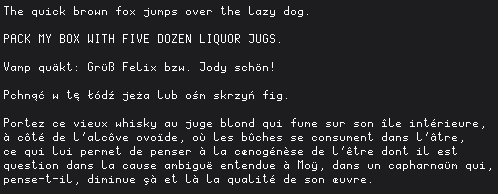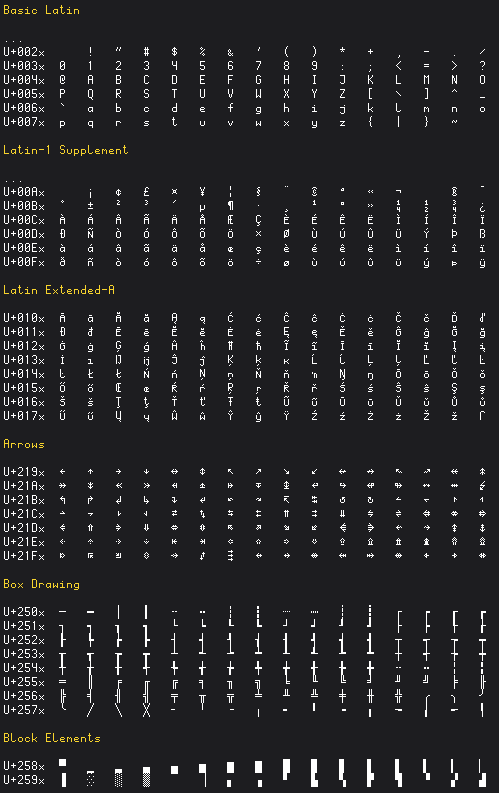
免费的微型Unicode等宽像素字体素材,一种是4×8的小字体,另一种是7×14的大字体。
小字体尽可能小,但仍能保证所有标准ASCII字符清晰可辨。大字体稍大一些,以便容纳其他语言的字符。
小字体
这是一个仅支持英文的(ASCII)字体。字符图块为 4×8 像素,但大多数字符可以容纳在 3×5 像素内。图像文件包含 128 列和 4 行字符(包括空格)。
按顺序排列的Unicode块
U+0000-U+007F,基础拉丁语
U+2190-U+21FF,箭头
U+2500-U+257F,箱体图
U+2580-U+259F,块元素
大字体
此字体包含来自各种“拉丁”字符集的额外字符,因此除了英语之外,它还可以用于多种语言。字符图块尺寸为 7×14 像素,但大多数字符可以容纳在 5×9 像素的范围内。图像文件包含 128 列和 5 行字符(包括空格)。
按顺序排列的Unicode块
U+0000-U+007F,基础拉丁语
U+00A0-U+00FF,拉丁语-1 补充(部分)
U+0100-U+017F,拉丁扩展A
U+2190-U+21FF,箭头
U+2500-U+257F,箱体图
U+2580-U+259F,块元素